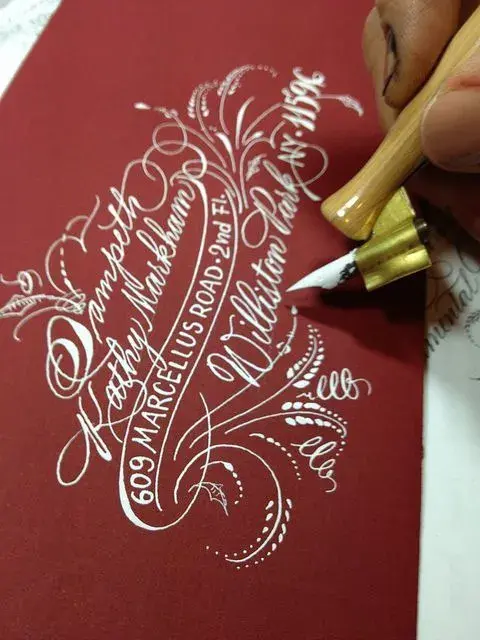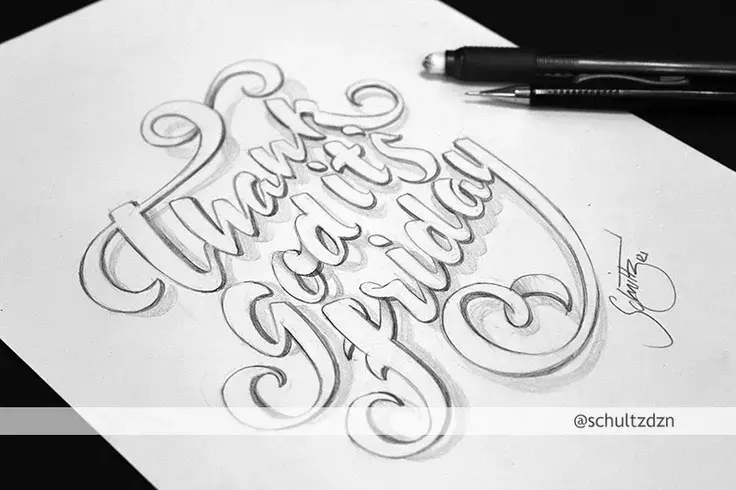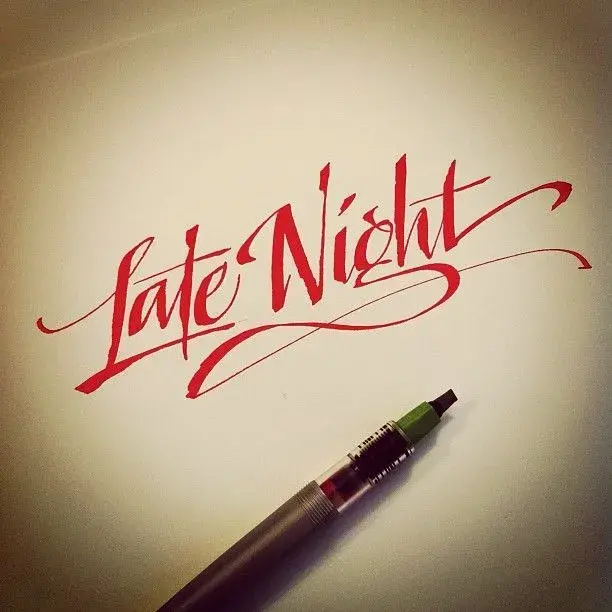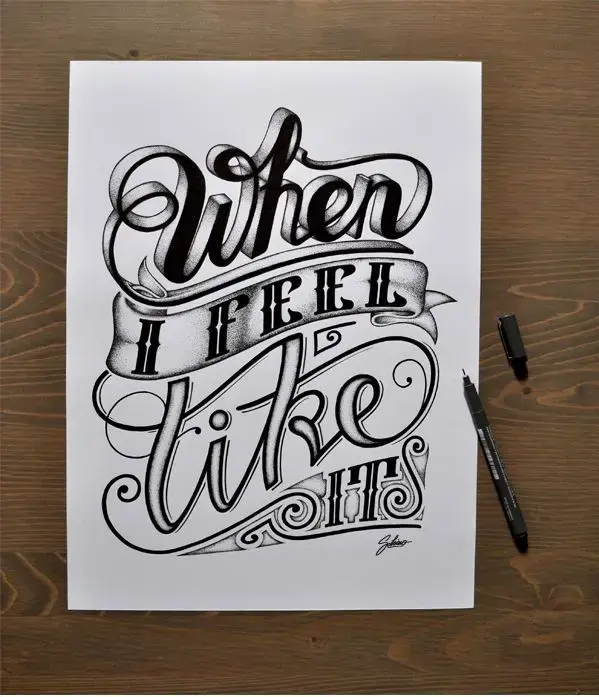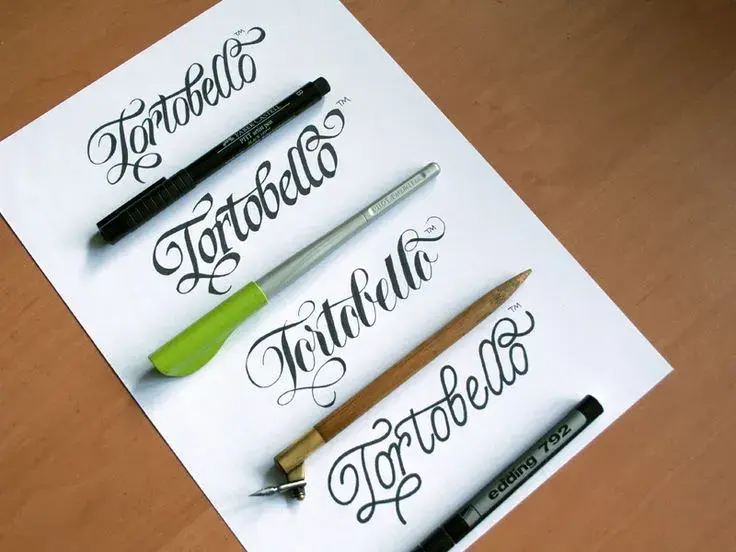
Maîtrisez l'Art du Lettering, de la Calligraphie et de la Typographie
Découvrez cette semaine le second numéro pour notre rendez-vous des inspirations typographiques avec une sélection autour du lettering et de la calligraphie.
Nous croisons de plus en plus sur les sites comme Dribbble ou Behance des réalisations autour des typographies réalisées à la main. Le rendu est très séduisant et donne des compositions dynamiques. Nous avons sélectionné une série non exhaustive avec des créations aux stylos, aux feutres et aux différents médiums pour la calligraphie afin de vous donner une jolie dose d'inspiration.
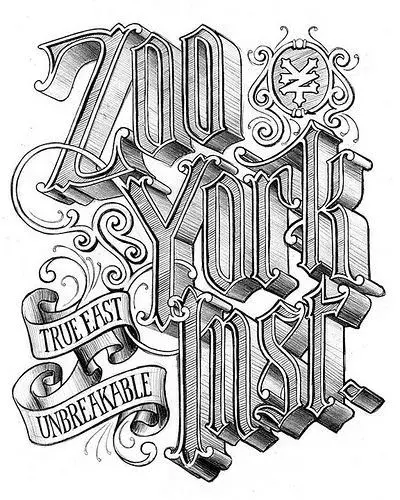
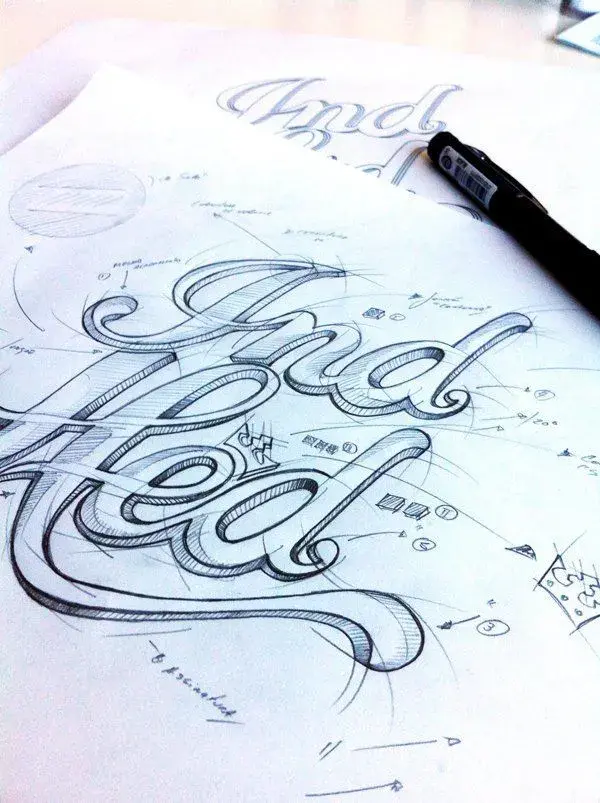Sans titre par Hachihawaii
IndHed™ Premium Craft Beer // Identity & Package Design
Iampeth envelope par Barbara Calzolari
Thank God It's Friday ! par Marcelo Schultz
Lettering par matthewtapia
Branthony Sketch par Colin Tierney
When I feel like it par Jérémy SCHIAVO
Tortobello pathfinder par Evgeny Tkhorzhevsky